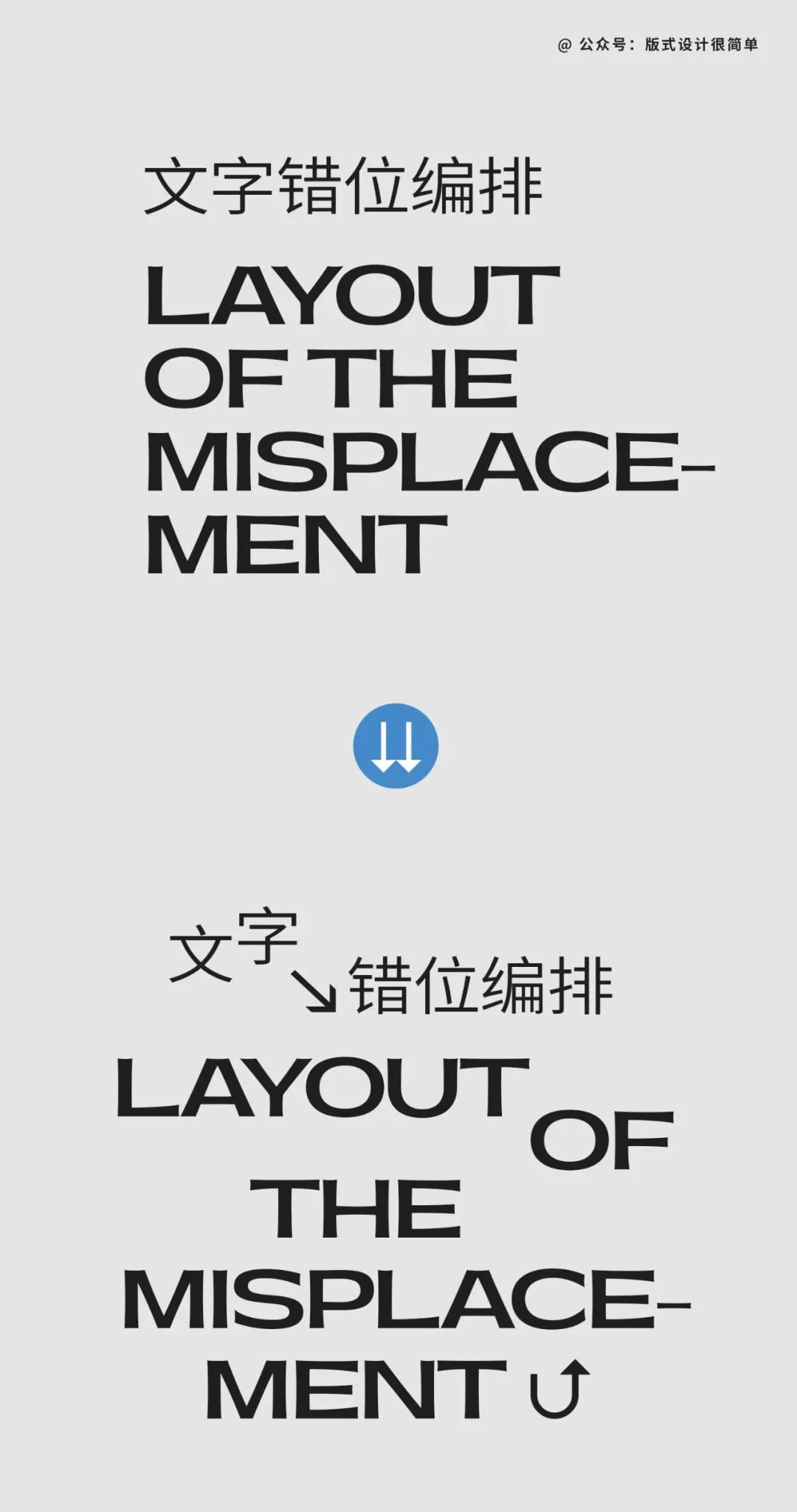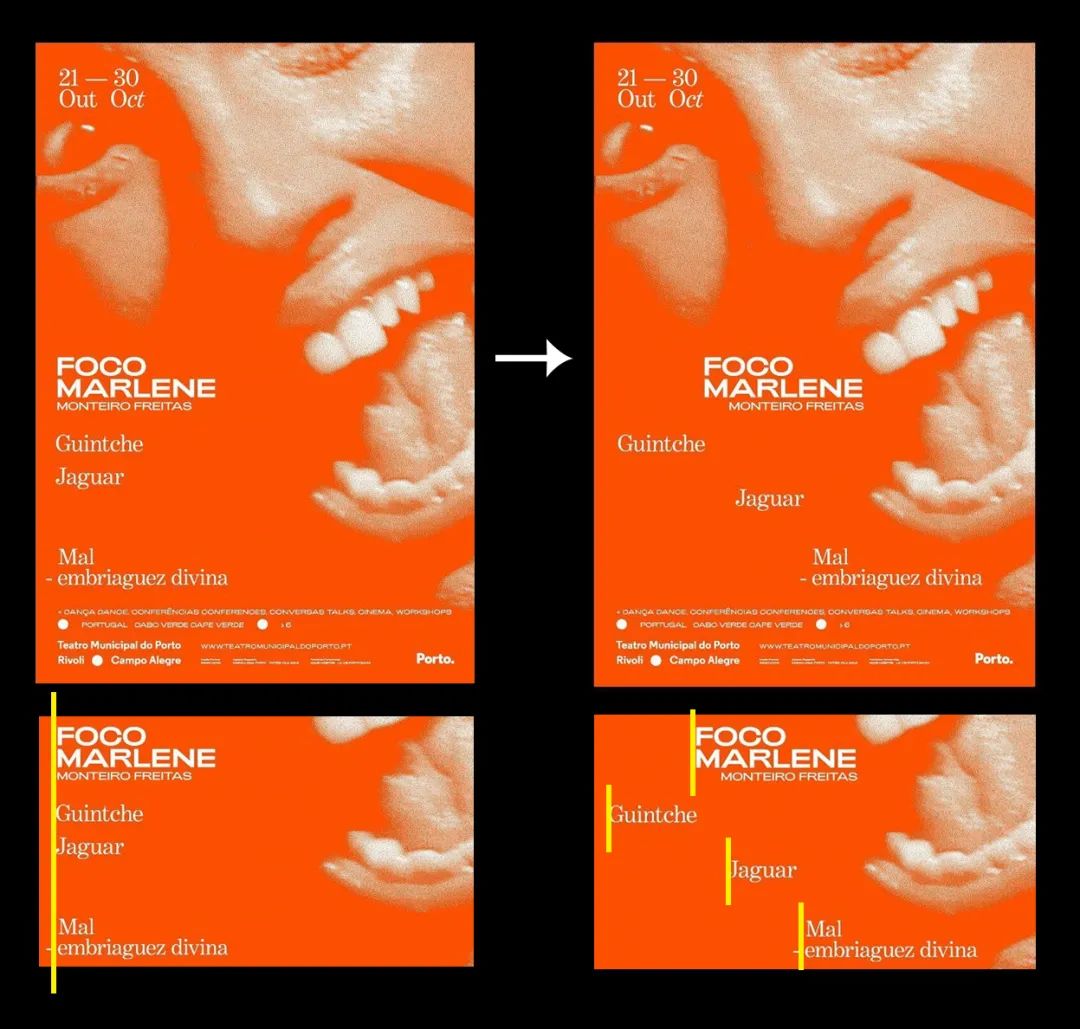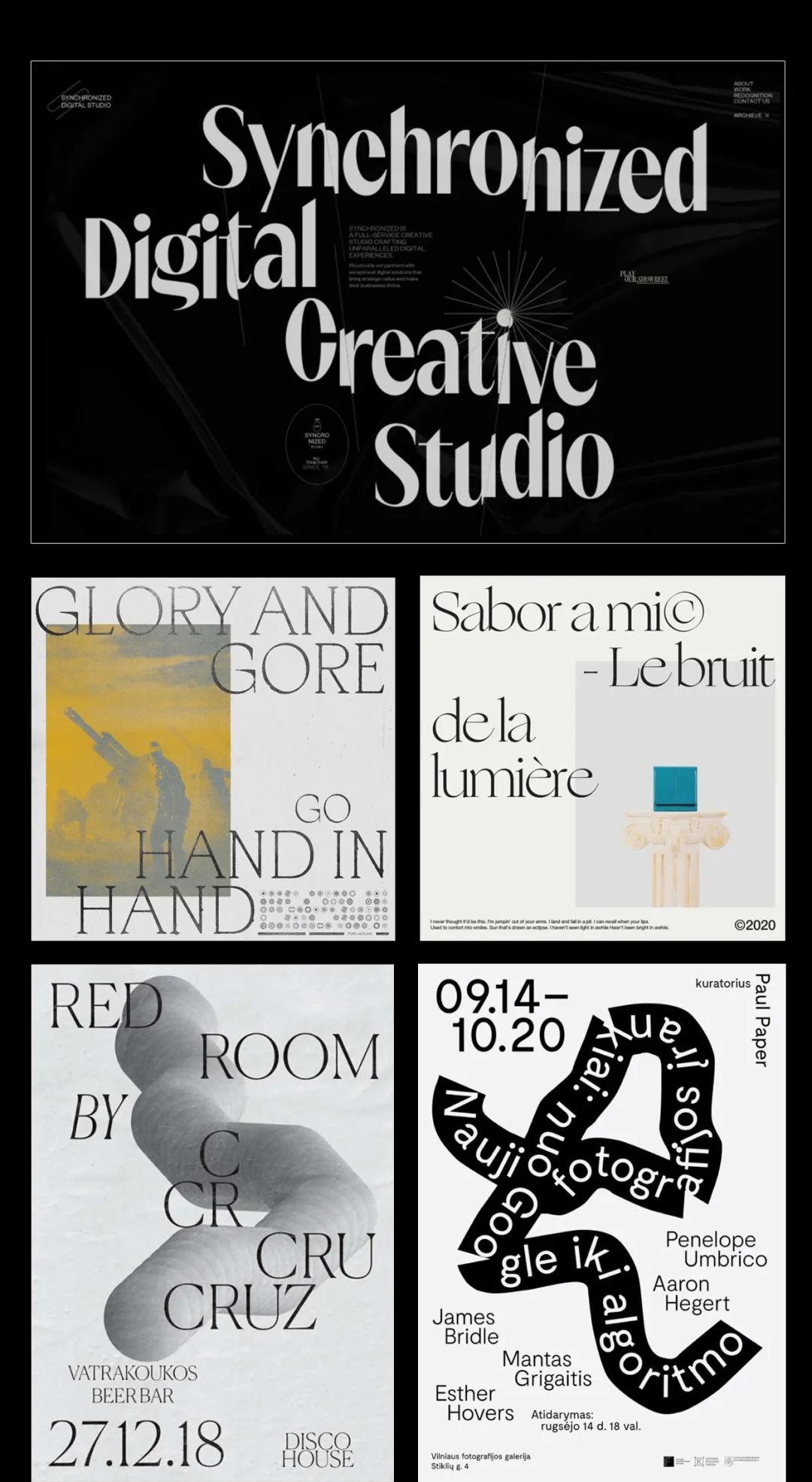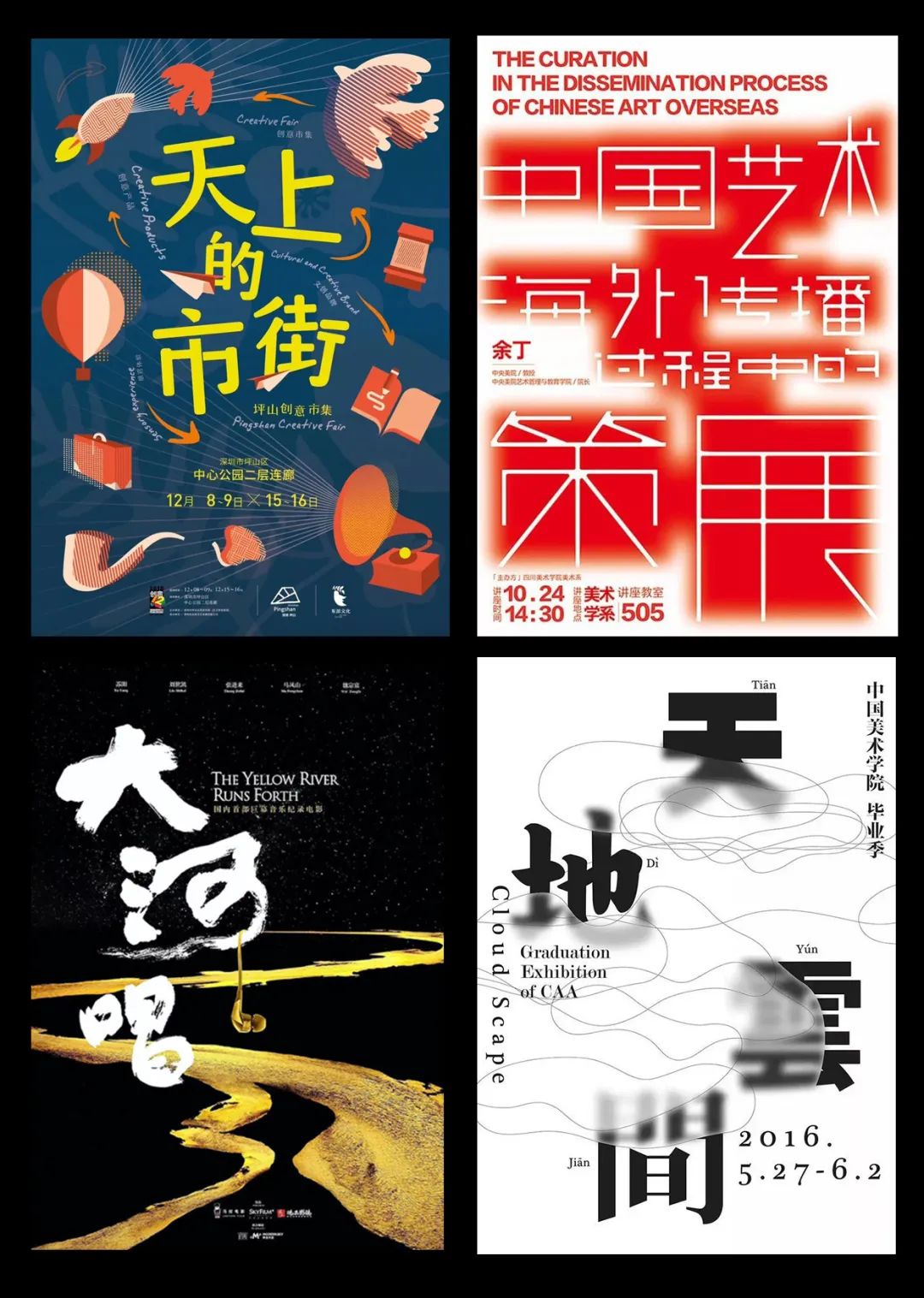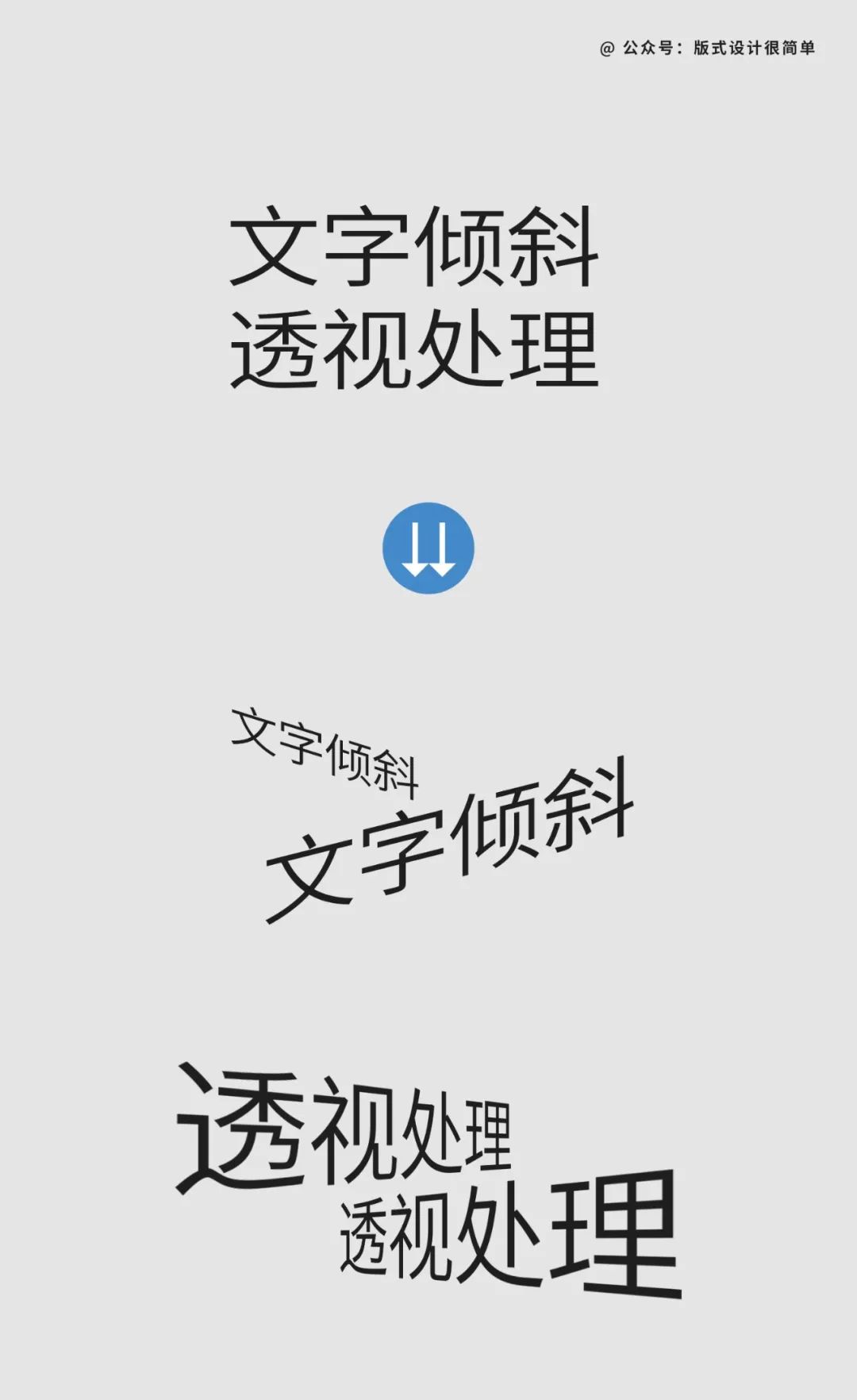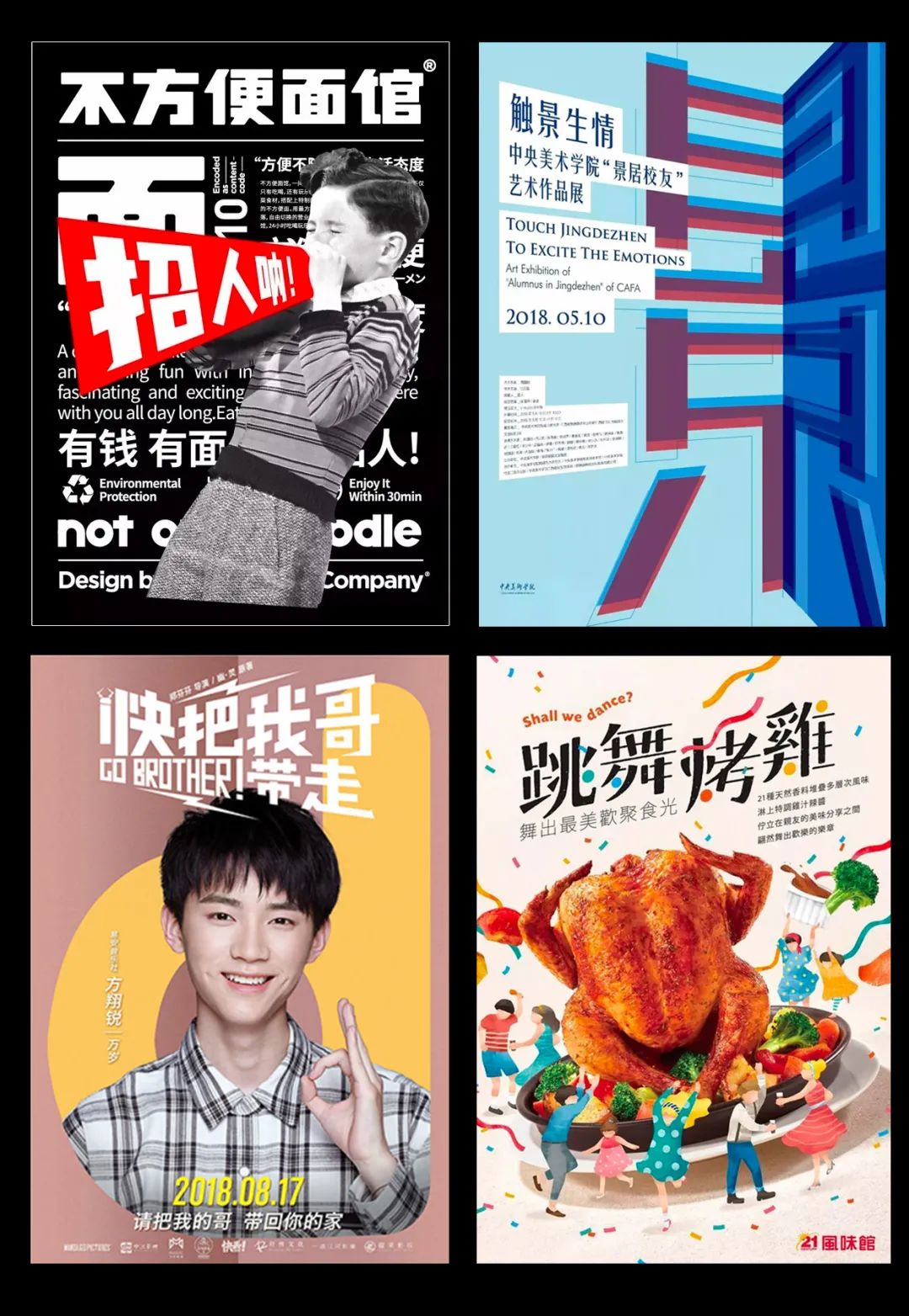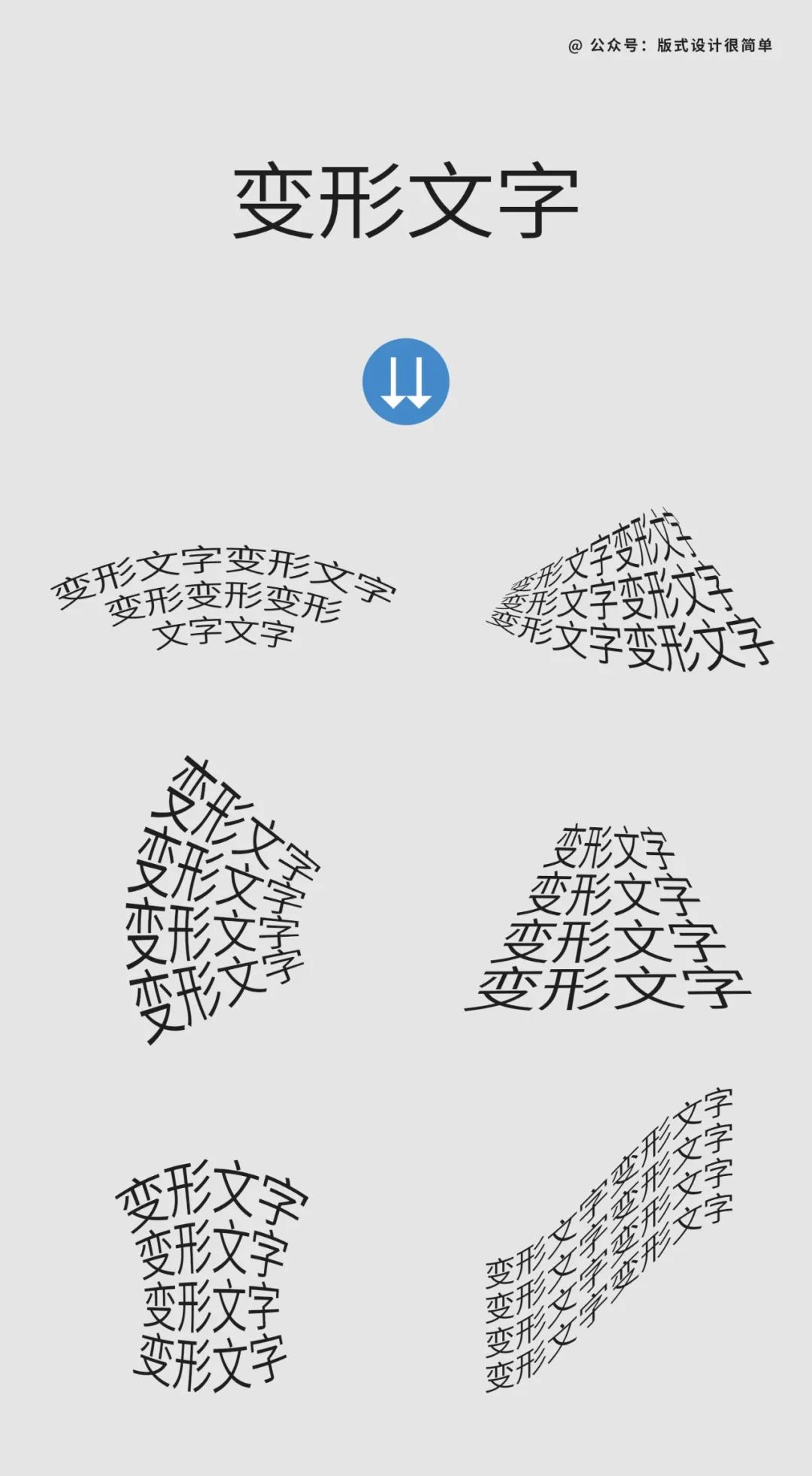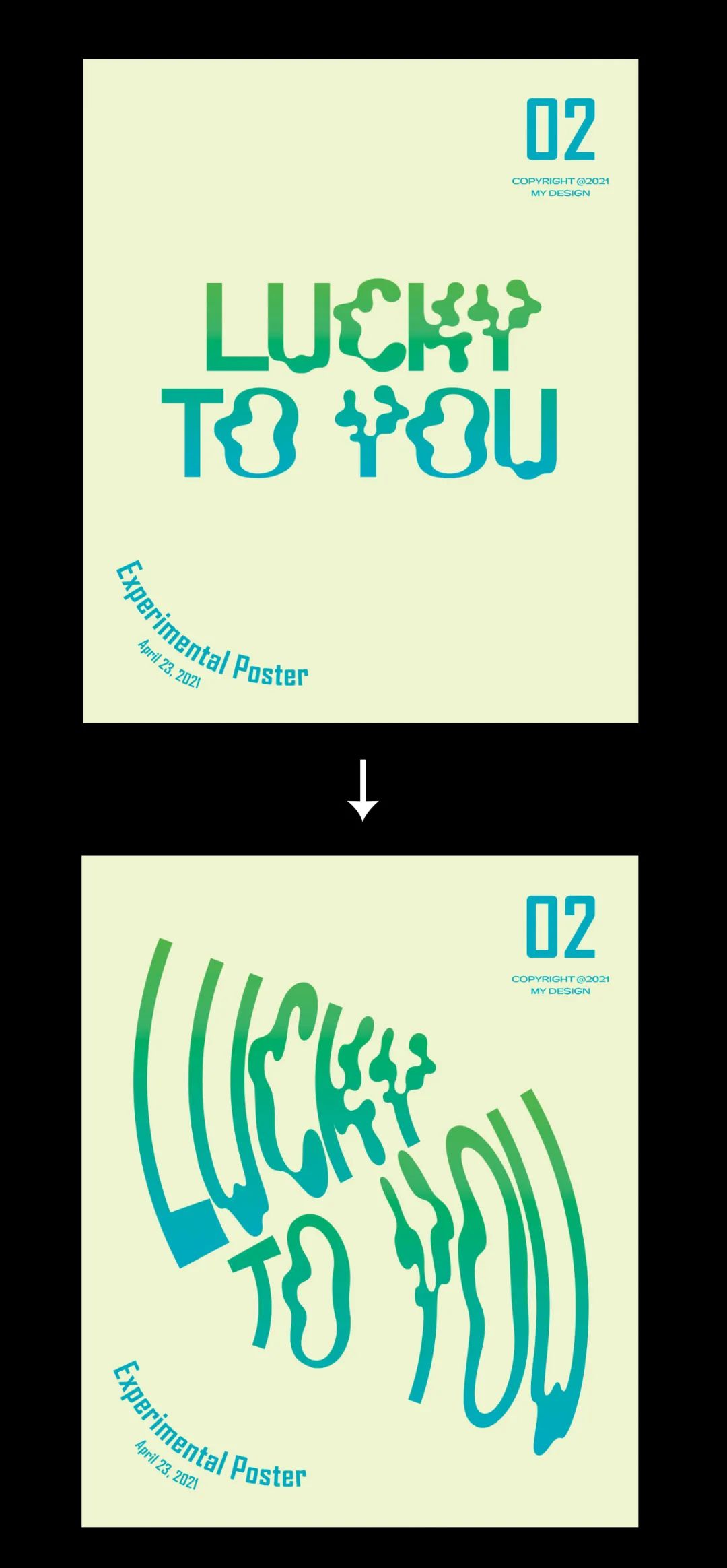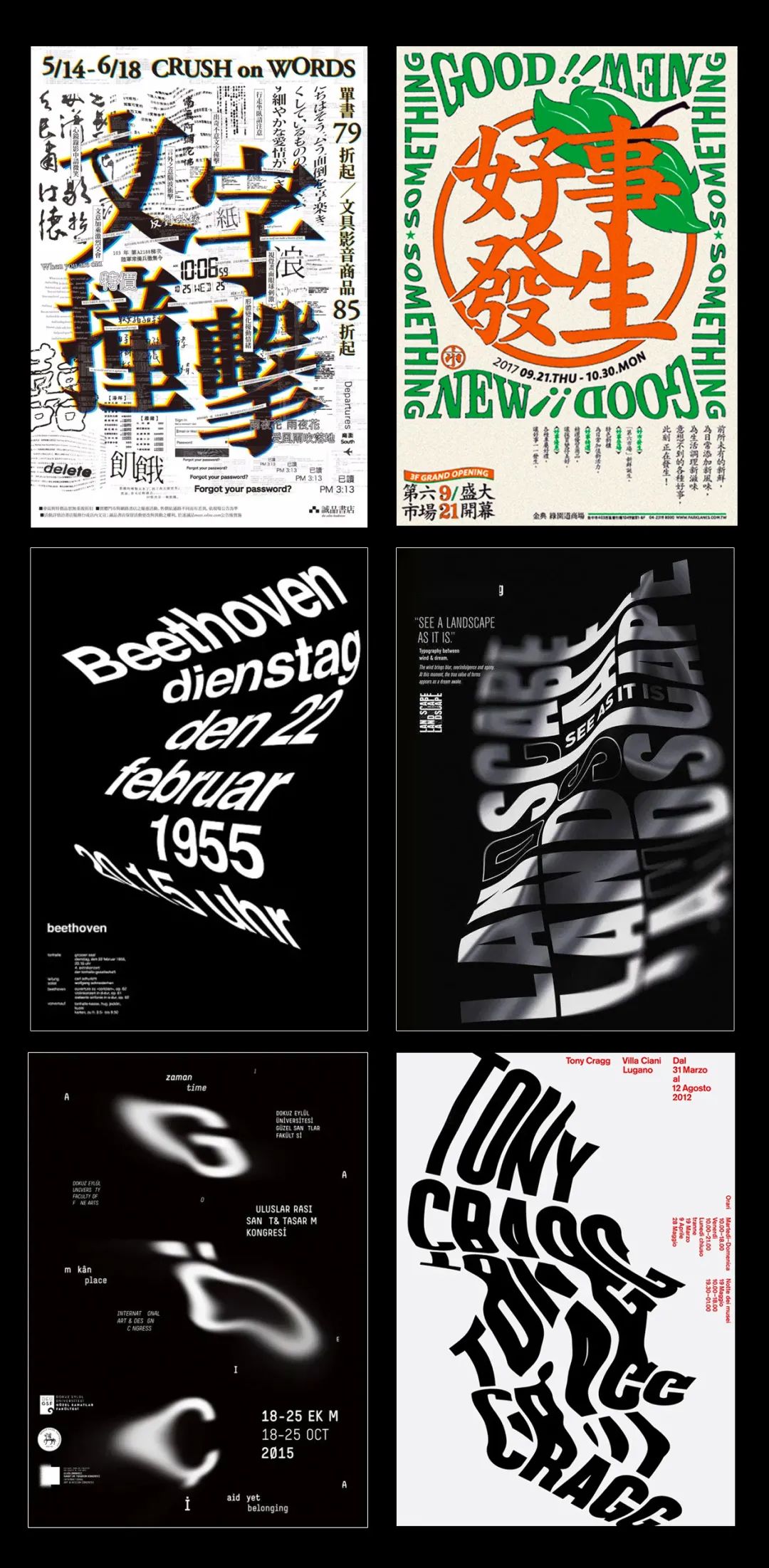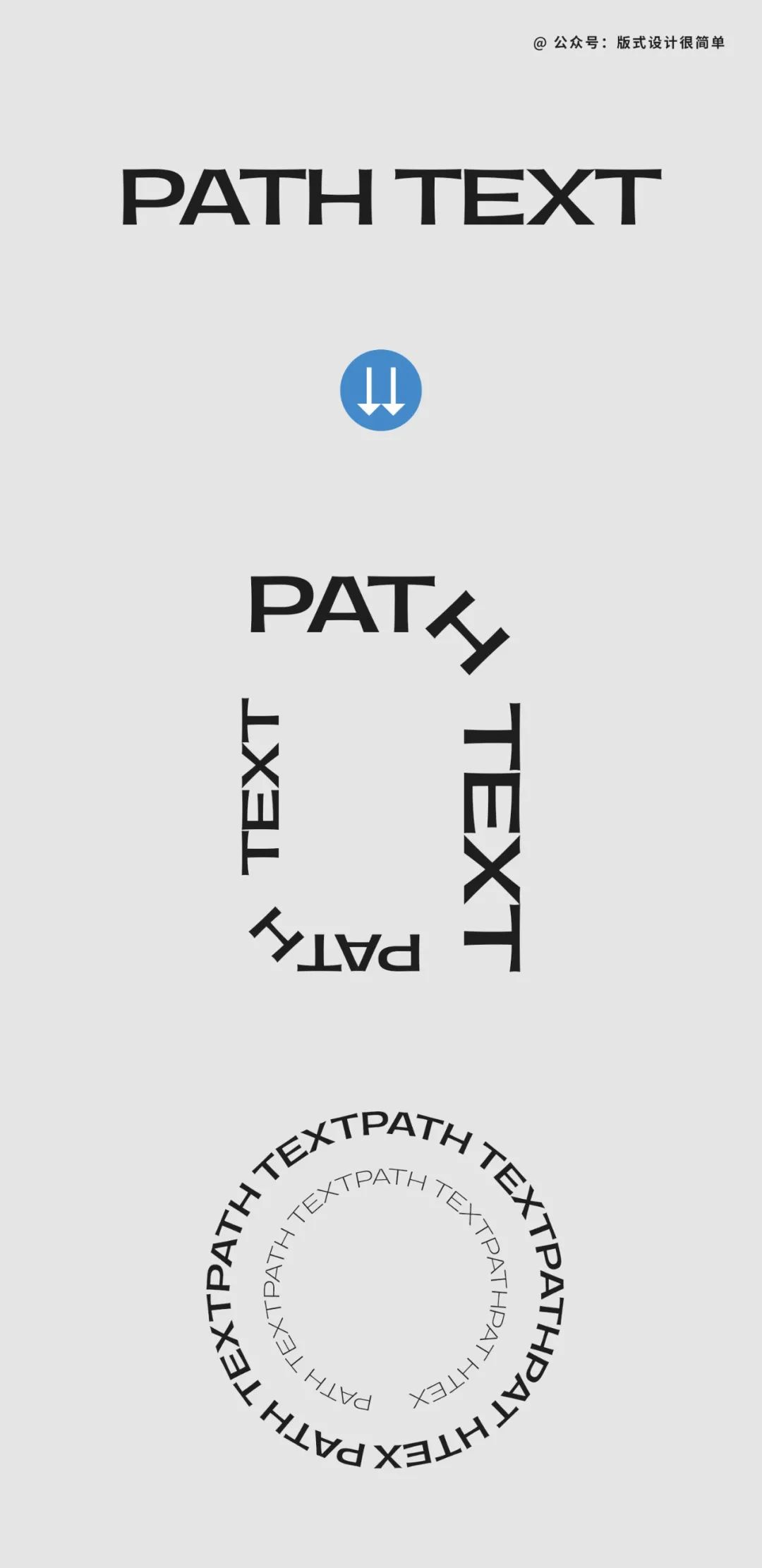
夏天到了,是时候让文字在画面中“游”起来了~
你是不是经常遇到这种情况,boss老说你的排版过于呆板,不够灵活?其实翻译过来就是对比不够强烈,没有视觉动感。今天就给大家整理了4种方法,希望能帮到你!
01⎘
文字错位编排
甲方接受程度:★★★☆☆
对于错位编排,相信大家早不陌生了。它是在对齐的基础上改变位置,能形成一定的留白和层次感。
虽然错位之后产生的视觉似乎有些凌乱,但如果将主次信息处理好,添加视觉符号或图形作为装饰引导,那么确实能瞬间改变常规,营造灵活感。
02⎘
倾斜或透视处理
甲方接受程度:★★★★☆
将文字整体或局部排列成倾斜状态,构成非对称的画面,或者做成透视感。
这样改变文字方向之后,就形成了强烈的视觉动感,表现出文字间的节奏感。
03⎘
变形文字
甲方接受程度:★★☆☆☆
如果想让文字更有流动性和艺术感,可以尝试将它变形,不同的动态表现,都会有不同的视觉效果。
只是需要注意变形的程度,不能影响到它的识别度和信息传达性。
04⎘
路径文字
甲方接受程度:★★☆☆☆
所谓路径文字就是沿着路径来编排文字,它不但可以使用在开放的路径,还能运用到封闭的路径中,尤其是近年的酸性风格。
除了以上四种方式,当然还有其他设计的技法。例如我们不改变文字,只改变颜色或图形带来的动感。